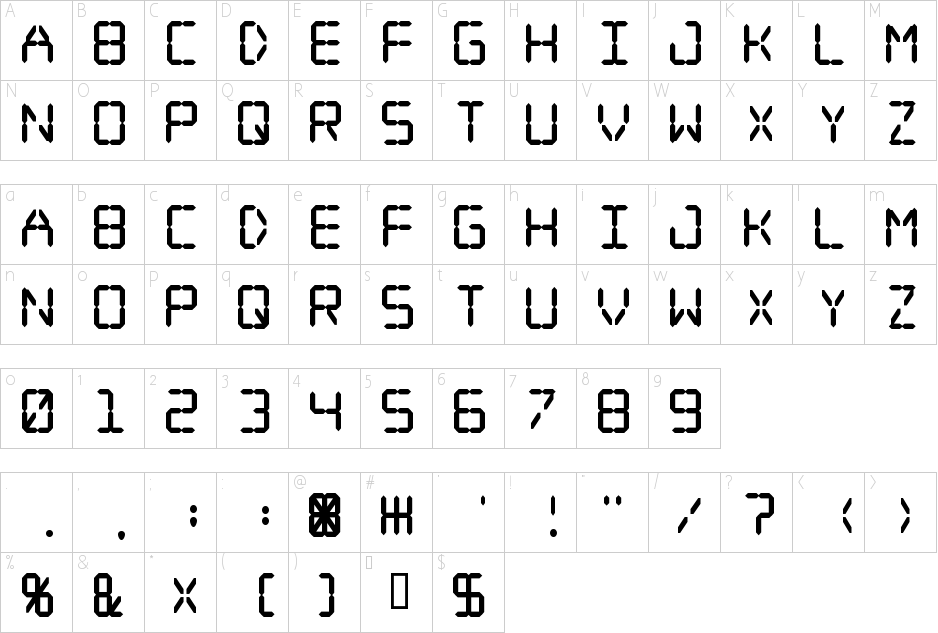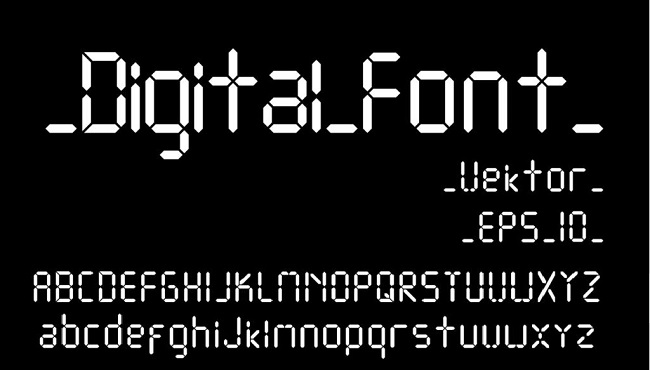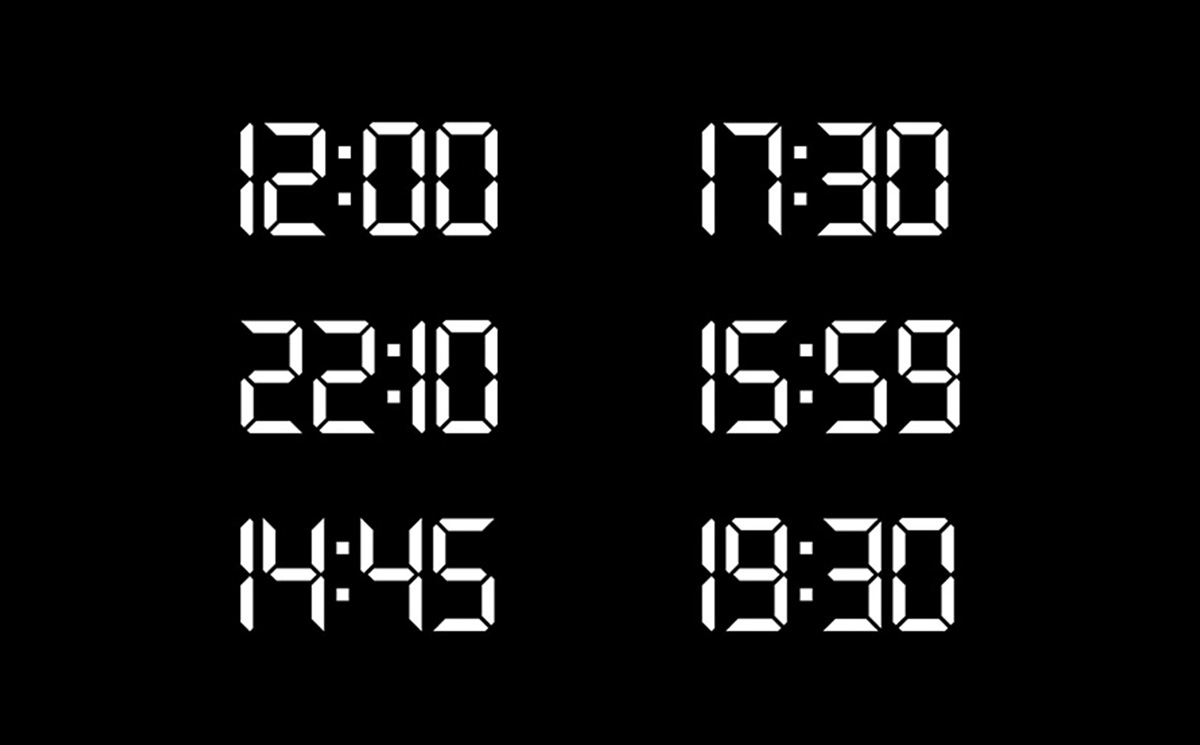
Font chữ đồng hồ điện tử – Tổng hợp font LED kỹ thuật số đẹp và hiện đại
Font chữ đồng hồ điện tử (thường được biết đến là dòng phông chữ LED Matrix hoặc 7-Segment Display) là nhóm phông chữ mô phỏng lại bảng hiển thị số trên các loại đồng hồ điện tử, máy tính bỏ túi và thiết bị đo đạc kỹ thuật số. Với đặc trưng là các đoạn thẳng ghép nối tạo thành chữ số vuông vức mang đậm phong cách Retro-Tech, nhóm phông chữ này là lựa chọn số một cho các thiết kế bao bì thiết bị công nghệ, đồng hồ thông minh, hộp quà tặng giới hạn (Countdown) và poster sự kiện công nghệ. Doozypack.vn cung cấp link download font chữ đồng hồ điện tử chuẩn kỹ thuật, giúp bạn sở hữu trọn bộ phông chữ độc đáo, hỗ trợ hiển thị số và tiếng Việt mượt mà khi thiết kế in ấn.
Đặc điểm thẩm mỹ độc đáo của bộ font chữ đồng hồ điện tử
Font chữ đồng hồ điện tử không đi theo sự uốn lượn mềm mại của chữ viết tay; nó tái hiện trọn vẹn sự chính xác của vi mạch điện tử và tư duy hiển thị số học thập niên 1980.
Mẫu chữ đồng hồ điện tử
Phong cách LED 7 đoạn (7-Segment Display) kinh điển và hoài cổ
Đặc trưng lớn nhất của Font số đồng hồ điện tử là mỗi ký tự số (từ 0 đến 9) được cấu thành từ 7 đoạn thẳng sáng tắt riêng biệt. Thiết kế này mô phỏng chân thực các bóng đèn LED hoặc màn hình tinh thể lỏng (LCD) đời đầu. Khi đặt phông chữ này làm tiêu đề hoặc hiển thị các mốc thời gian trên bao bì, sản phẩm của bạn sẽ ngay lập tức toát lên vẻ hoài cổ (Retro-futuristic), công nghệ và kích thích sự tò mò của người tiêu dùng.
Cấu trúc số góc cạnh mang đậm dấu ấn công nghệ số
Các ký tự của phông chữ đồng hồ điện tử sở hữu góc vuông 90 độ dứt khoát, cấu trúc lưới điện tử đều đặn tạo nên một nhịp điệu Typography vô cùng ngăn nắp. Phong cách này mang lại cảm giác kỹ thuật, chính xác và minh bạch, cực kỳ ăn ý với các thương hiệu muốn nhấn mạnh vào tính năng thông minh, thời gian thực hoặc hiệu suất của sản phẩm.
Ưu điểm nổi bật của bản phông chữ đồng hồ điện tử Việt hóa
Khi ứng dụng các phông chữ kỹ thuật số vào thiết kế thương mại trong nước, sự chỉn chu về các ký tự phụ và bảng chữ cái tiếng Việt là yếu tố quyết định đến tính chuyên nghiệp của ấn phẩm:
• Hỗ trợ đầy đủ số và bảng chữ cái: Không chỉ dừng lại ở các chữ số LED quen thuộc, phiên bản tổng hợp tại Doozypack.vn còn cung cấp đầy đủ bảng chữ cái Latinh và các dấu thanh tiếng Việt được thiết kế theo đúng tỷ lệ lưới điện tử (Digital Grid), bảo đảm sự đồng bộ tuyệt đối khi dàn trang.
• Bảo đảm tính đồng nhất thương hiệu: Việc sử dụng Font đồng hồ điện tử chuẩn giúp bạn tự tin dàn trang tiêu đề hoặc thông số mà không lo hiện tượng lỗi ô vuông hay nhảy về font hệ thống khô khan.
Kiểu chữ hiển thị kỹ thuật số
• Tem nhãn dán linh kiện điện tử: Cấu trúc số rõ ràng giúp các bảng thông số đo lường trên tem decal trở nên dễ tra cứu và chuyên nghiệp hơn cho người tiêu dùng.
Lưu ý kỹ thuật khi in ấn với phông chữ dạng đoạn LED điện tử
Việc sản xuất bao bì thực tế sử dụng các phông chữ kỹ thuật như font LED đòi hỏi sự am hiểu kỹ thuật chuyên sâu tại xưởng in Doozypack.vn:
• Kiểm soát khoảng cách giữa các đoạn LED: Các khe hở nhỏ giữa các thanh LED có thể bị lấp đầy nếu in ở kích thước quá nhỏ trên giấy thô. Bạn nên giữ size chữ số tối thiểu từ 10pt trở lên để bảo đảm hiệu ứng màn hình điện tử rõ ràng.
• Phối hợp màu sắc Neon công nghệ: Phong cách LED đẹp nhất khi in màu rực rỡ như xanh lá Neon, cam sáng hoặc đỏ điện tử trên nền hộp màu đen nhám.